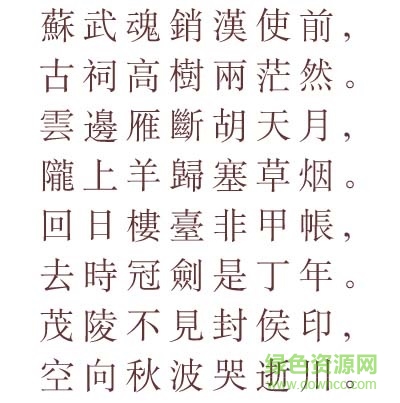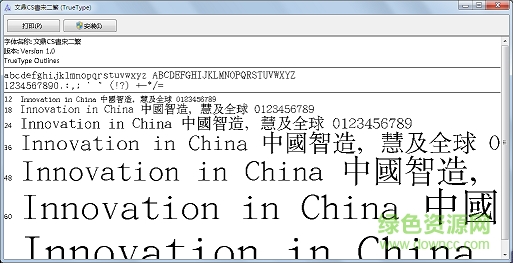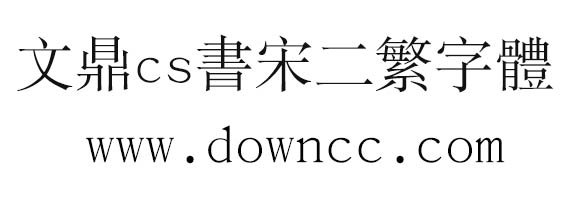
文鼎cs書宋二繁字體
文鼎cs書宋二繁是一款方正的繁體字體,屬于文鼎字體庫(kù)中的一種,使用范圍不是那么廣,有需要朋友,趕快去綠色資源網(wǎng)下載體驗(yàn)吧!
文鼎cs書宋二繁介紹
文鼎cs書宋二繁是問(wèn)鼎字體中的一種,書寫的筆畫很穩(wěn),并且線條很細(xì),適用用于很多地方